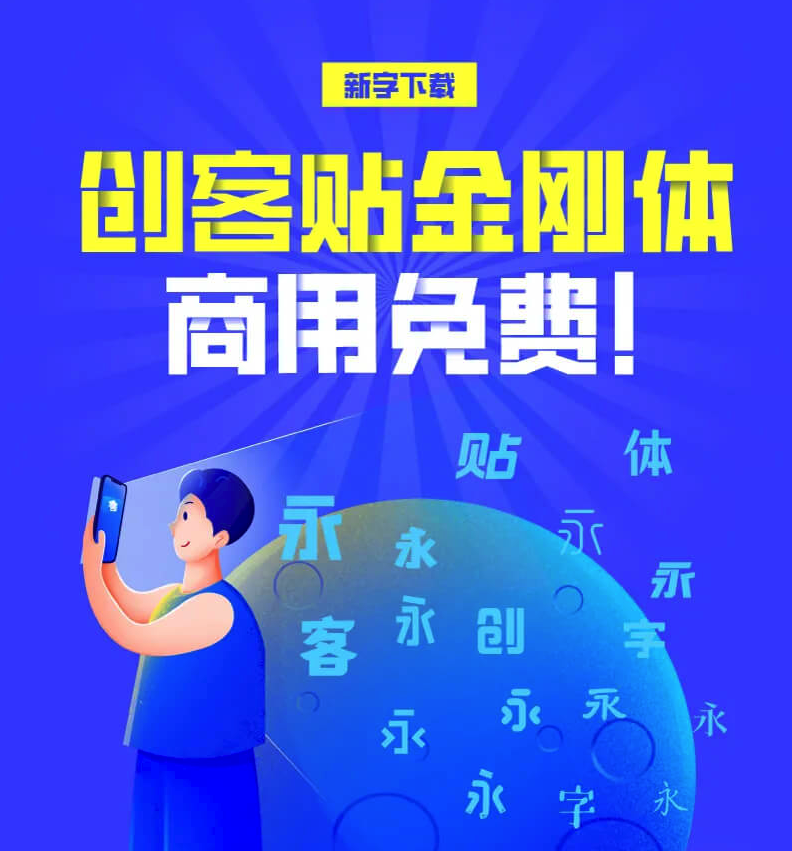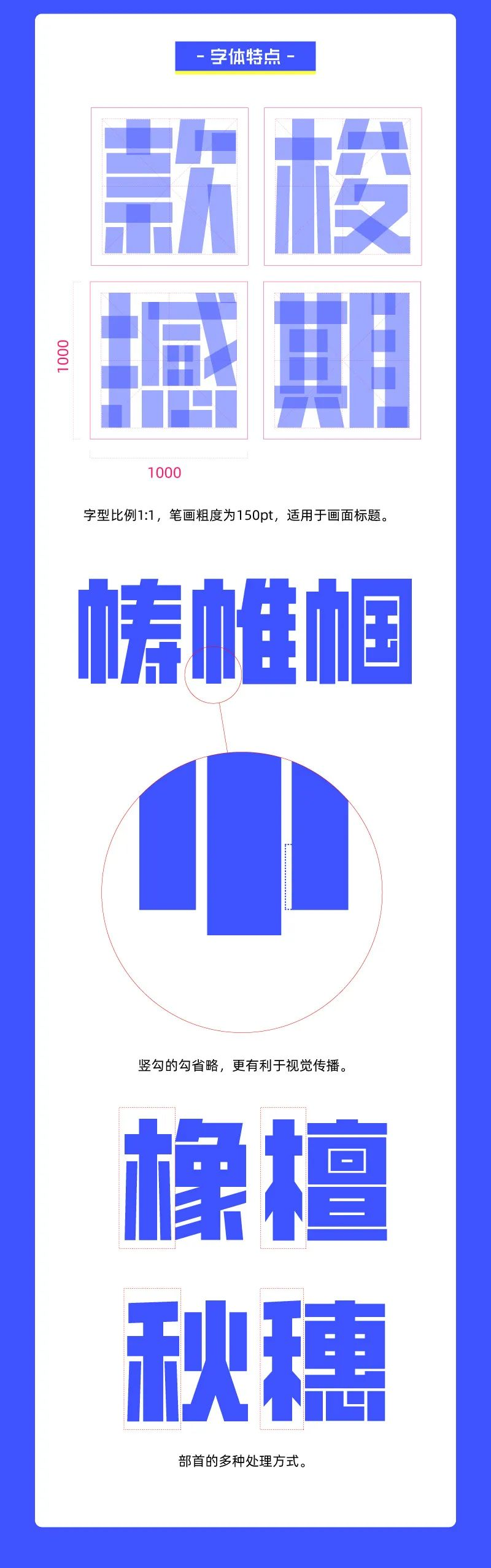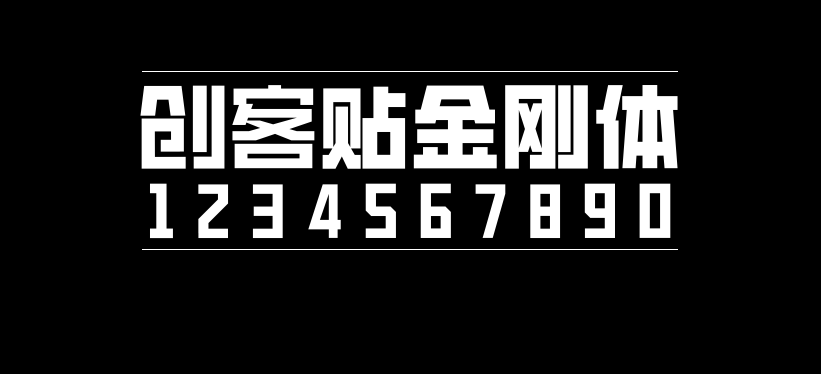
创客贴金刚体
创客贴金刚体是设计平台创客贴(知名字体设计师郑庆科旗下)为支援抗击疫情而创作的字体,之前只在 创客贴 ckt.cn 上架了这款字体,名称为“创客贴战疫体”。字体于2020年2月份上线,受到了用户的极大欢迎,我们也很高兴能够做出这么一点小小的贡献。现在我们将字体安装包开放下载,商用免费!
创客贴金刚体已覆盖标准简体6763字,满足日常用字需求。